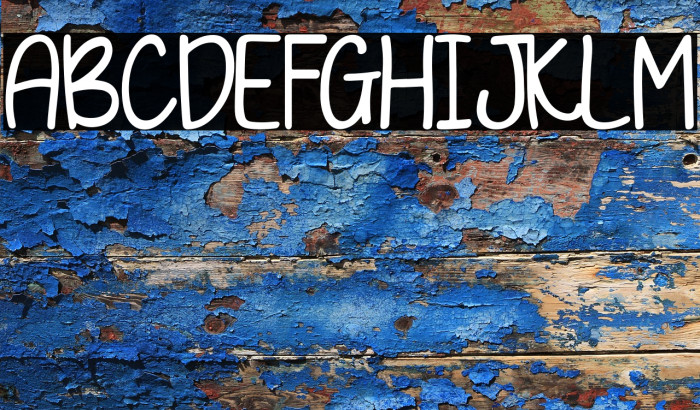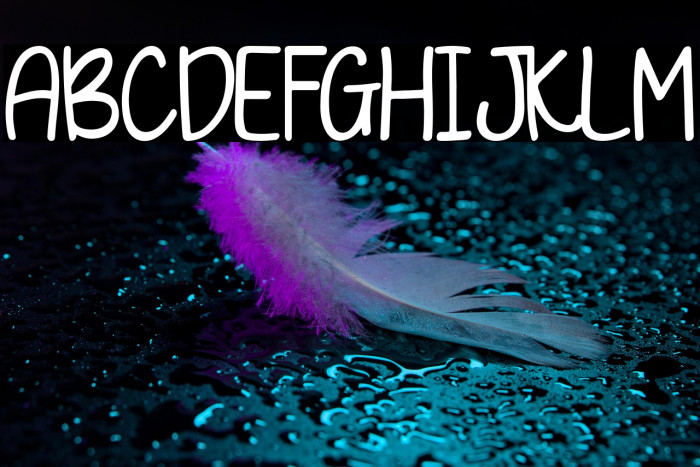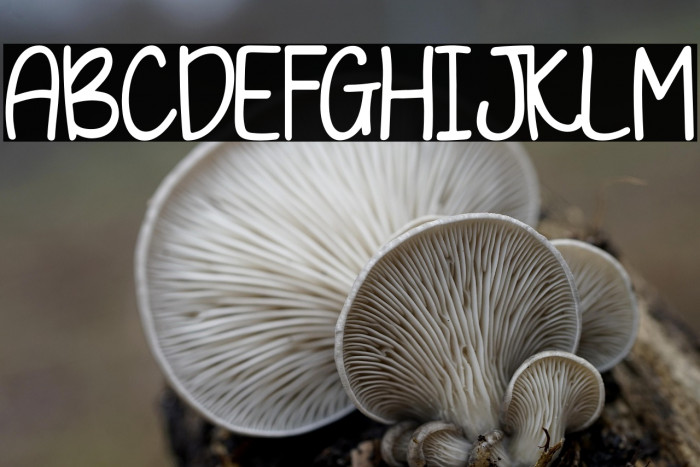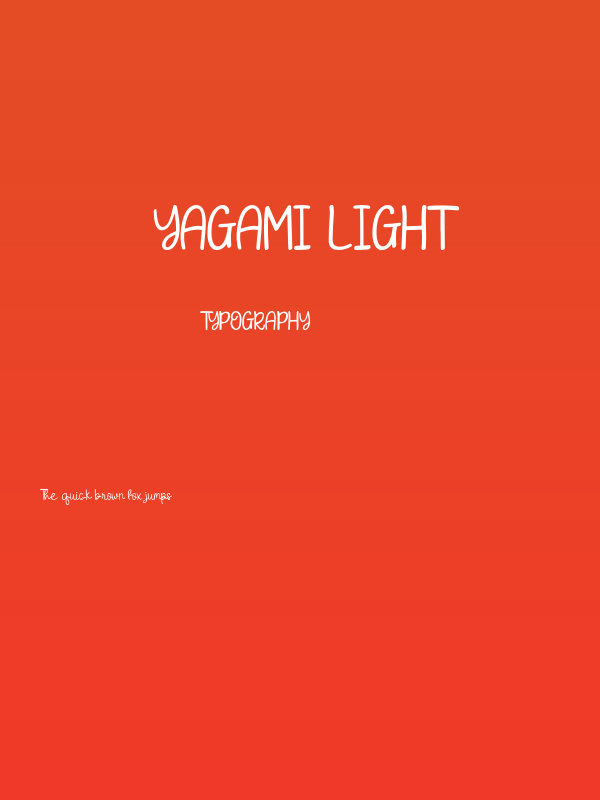
Yagami Light Font
| النمط العام | Casual, Playful |
| حالة الاستخدام | Logos, Headlines, Invitations |
| مشاريع مقترحة | Ideal for greeting cards, invitations, personal branding, and creative social media graphics. |